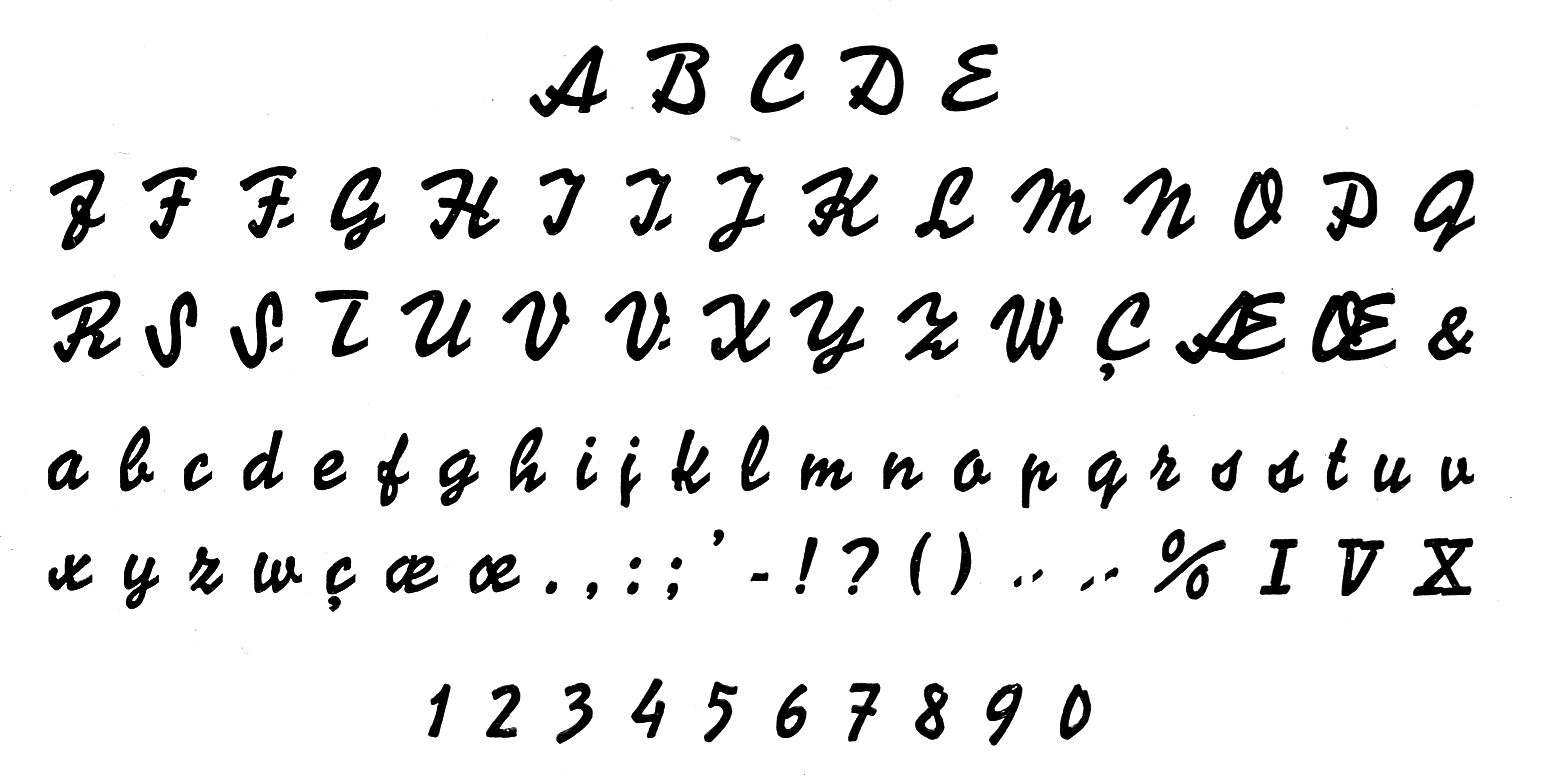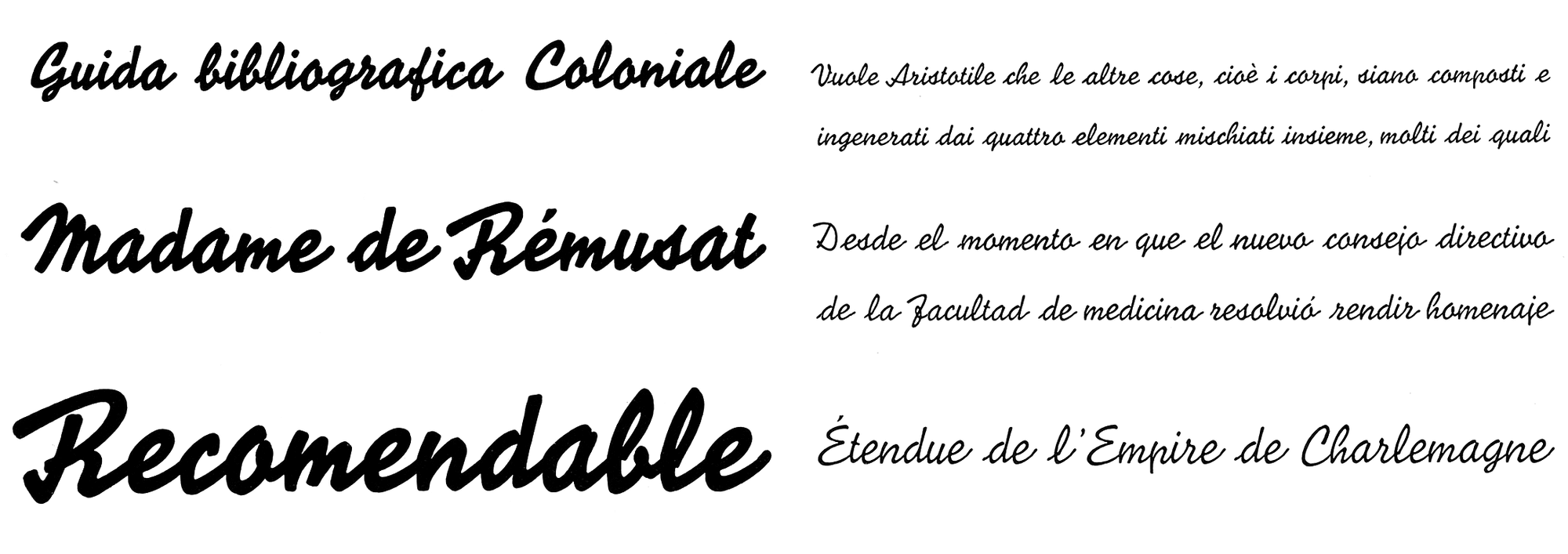
• 1934
• Antiqua Schreibschrift
Die Veltro ist eine italienische Werbeschreibschrift in zwei Strichstärken und wurde Anfang der 1930er-Jahre unter der Leitung von Giulio da Milano bei Nebiolo entwickelt. Das Design folgt den kurz zuvor in Deutschland erschienenen Schriften Energos (Schriftguß) und Signal (Berthold). Insbesondere die Kleinbuchstaben der fetten Veltro sind stark an die Signal angelehnt. Die Großbuchstaben zeigen dagegen deutlichere Eigenheiten.
Eine Digitalisierung beider Strichstärken gibt es unter dem Namen Veltro von Profonts.